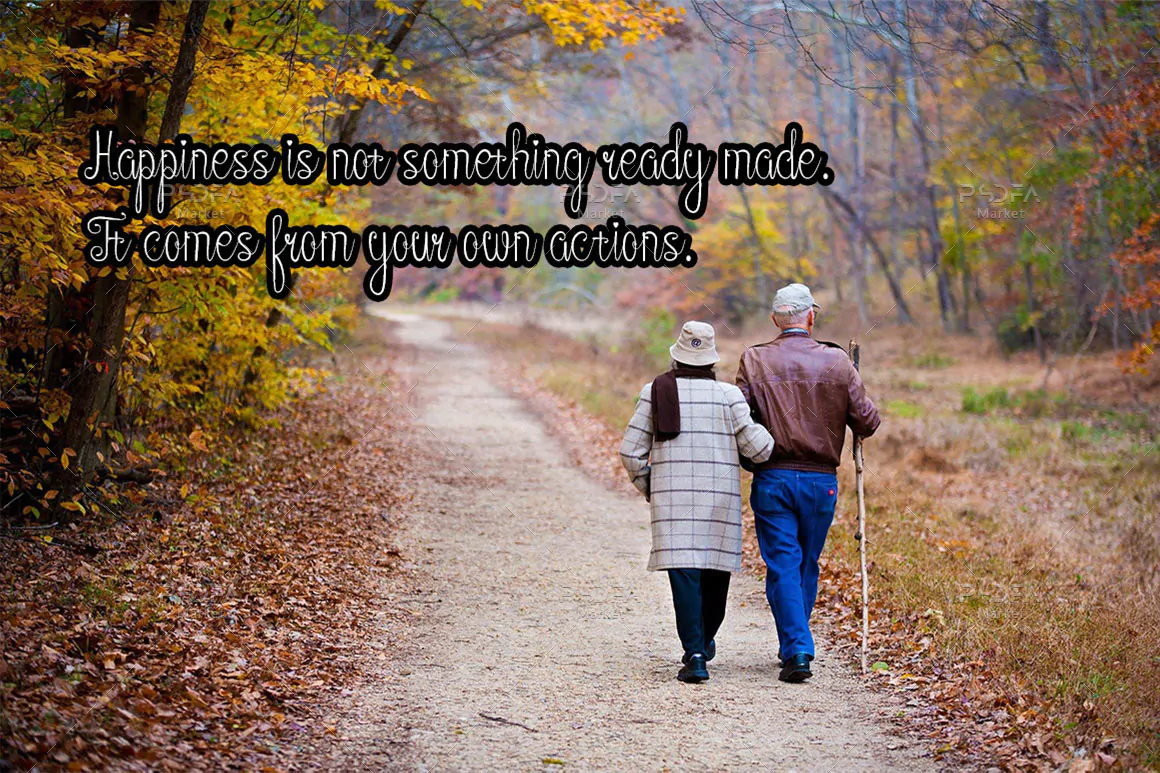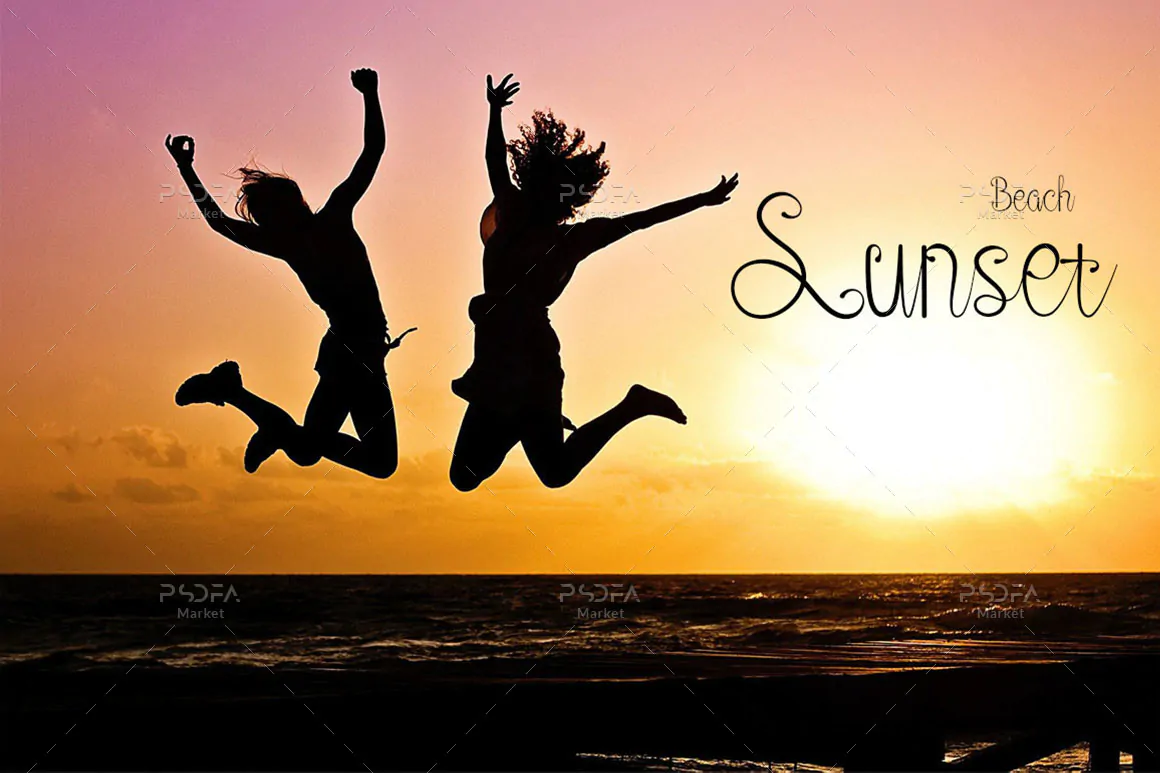
فونت دستنویس Nitalia
فونت دستنویس Nitalia یک اسکریپت فونت انگلیسی است که مناسب جهت استفاده در طرح و پروژههای گرافیکی مختلف میباشد. این فونت زیبا با وزن معمولی طراحی شده است که میتوانید از آن در طراحی انواع کارت تبریک، طرحهای رمانتیک و عاشقانه، بسته بندی محصولات، پوستر، قاب عکس، پست و استوری رسانههای اجتماعی و … استفاده کنید.